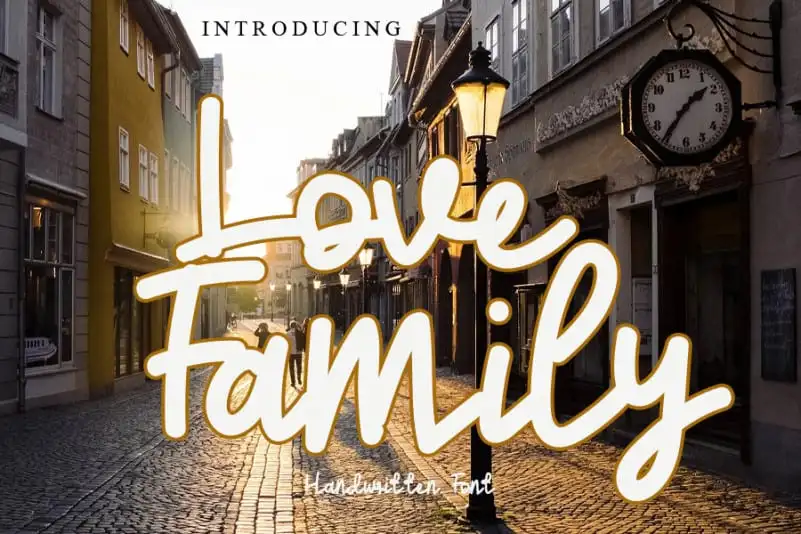
Love Family Handwritten Font – Download Grátis
A “Love Family Handwritten Font” é uma opção perfeita para quem busca uma fonte elegante e descontraída. Escrevendo com uma mão firme, essa fonte transmite um toque carinhoso e amigável que se encaixa em uma ampla variedade de projetos. Seu estilo natural e único a tornam perfeita para criar designs únicos e memoráveis. Não há limites à sua criatividade com esta fonte – seu design quase parece ter vida própria, criando interações interessantes semelhante a um diálogo entre pais e filhos. Ideal tanto para projetos pessoais quanto profissionais, essa fonte é uma escolha inteligente para aqueles que valorizam a personalização em cada projeto.